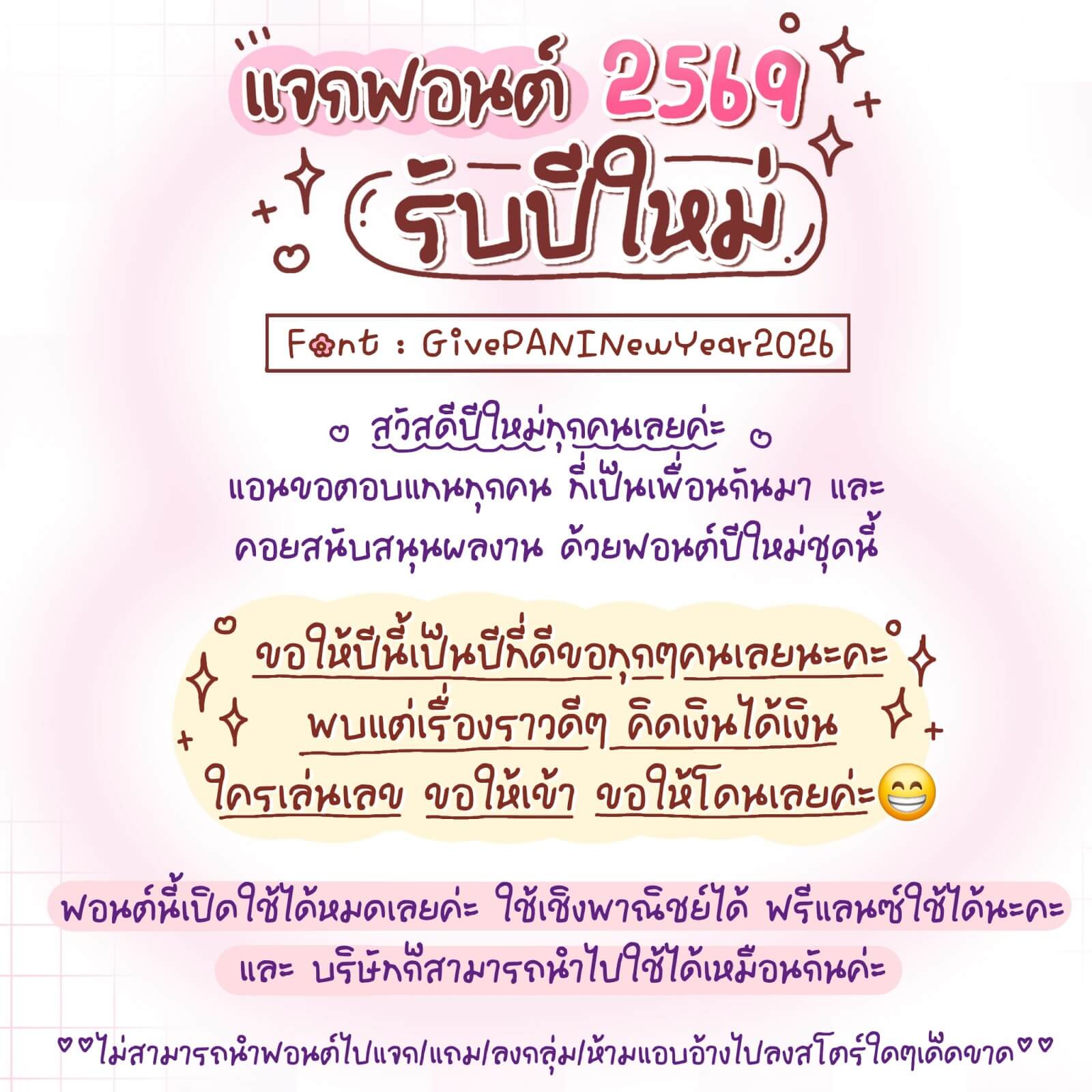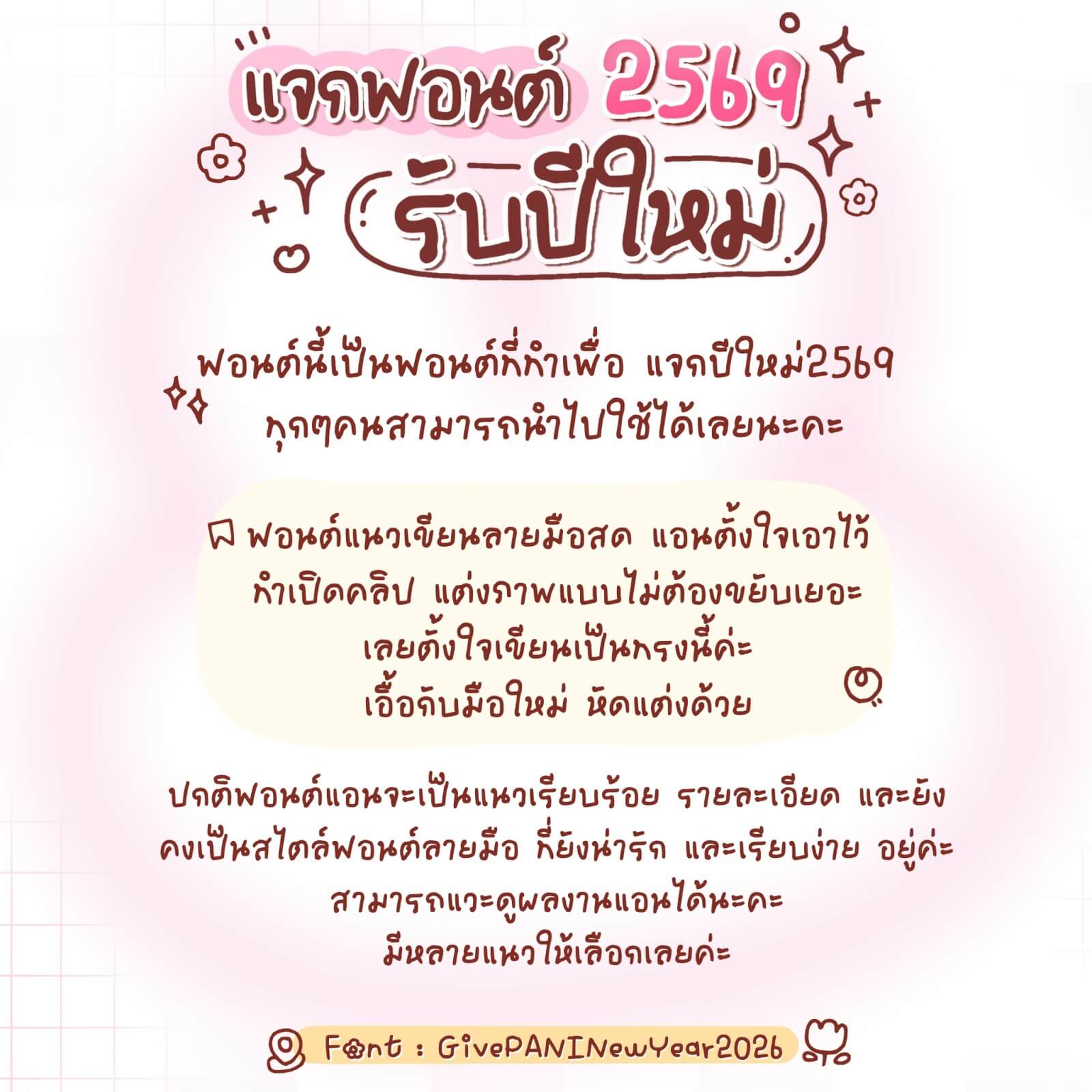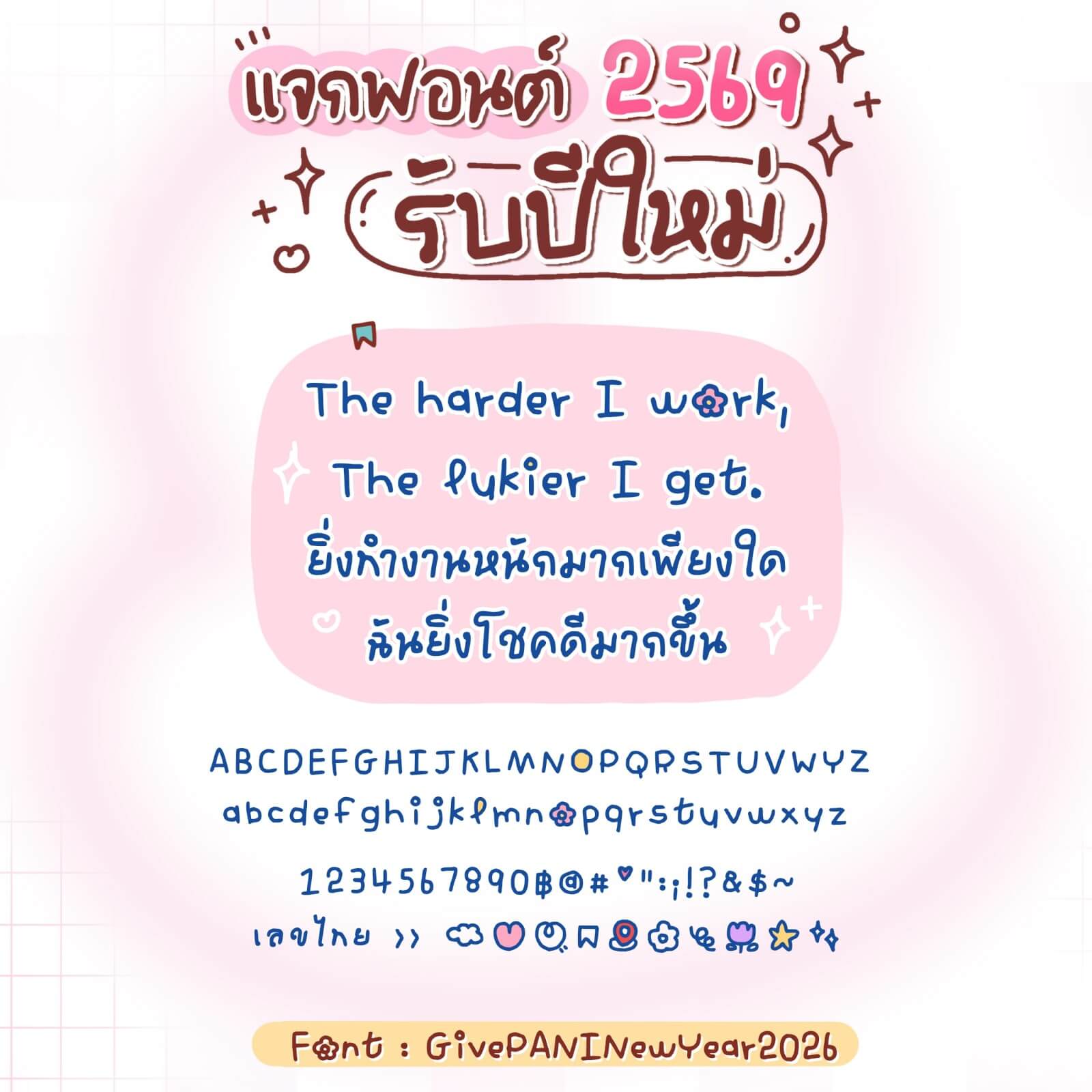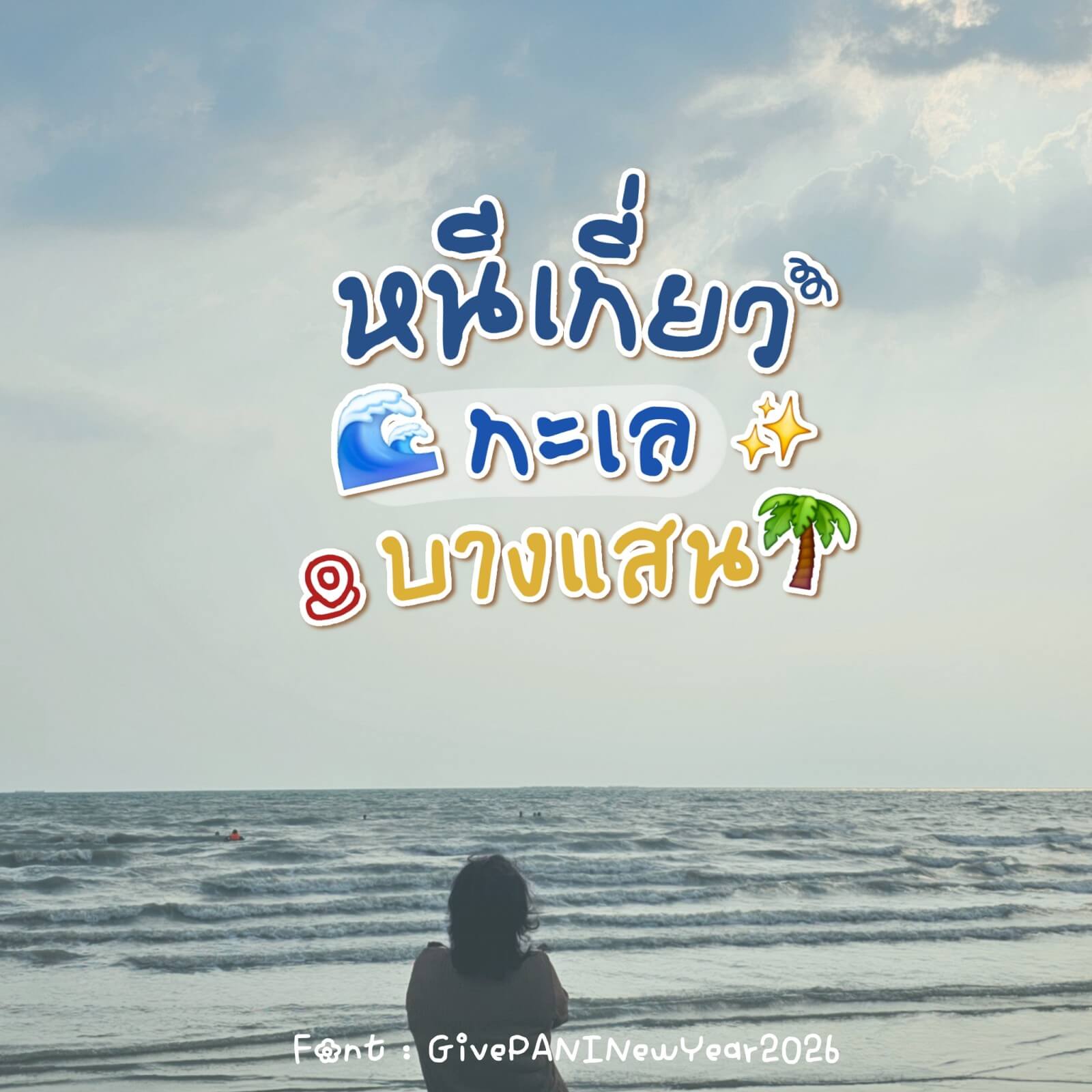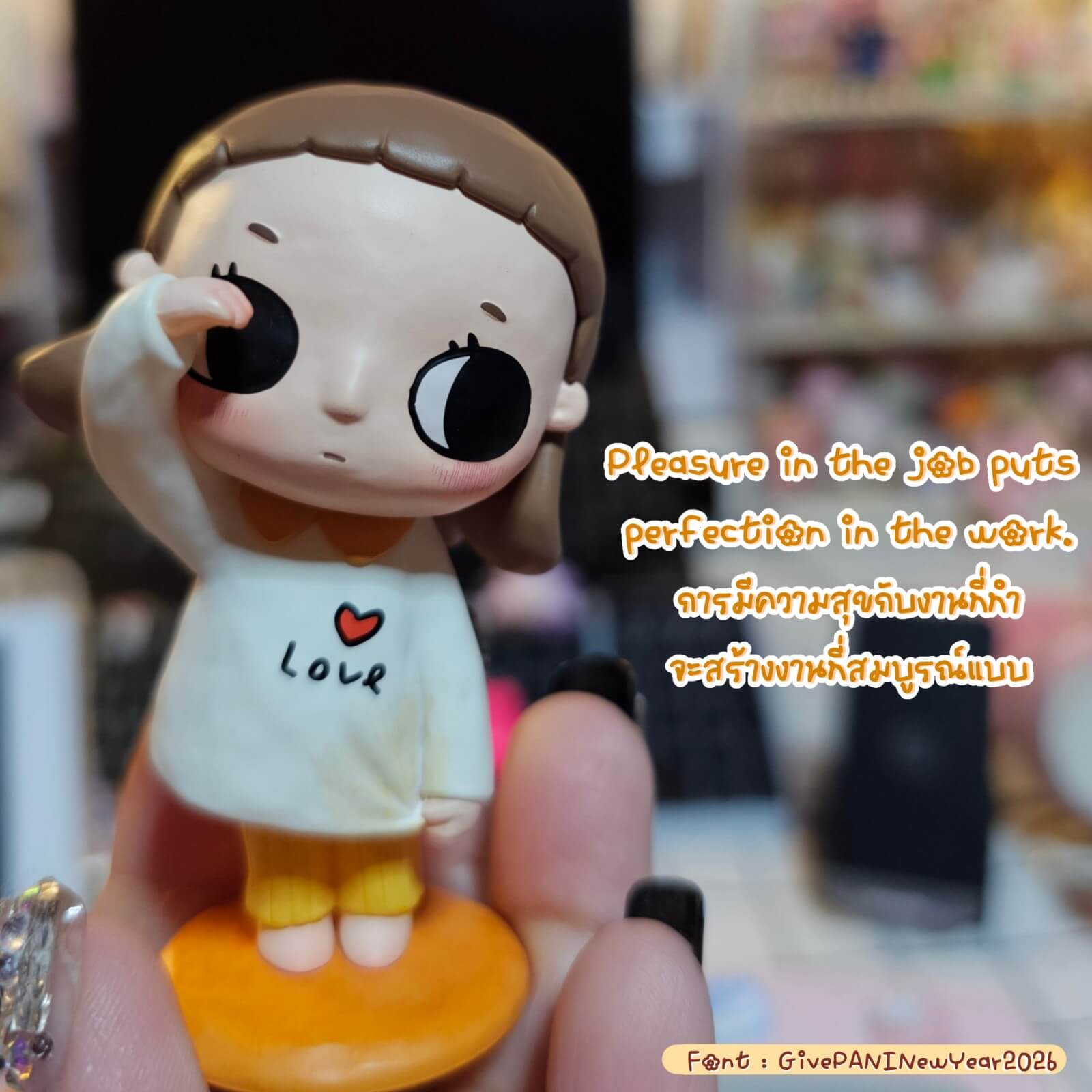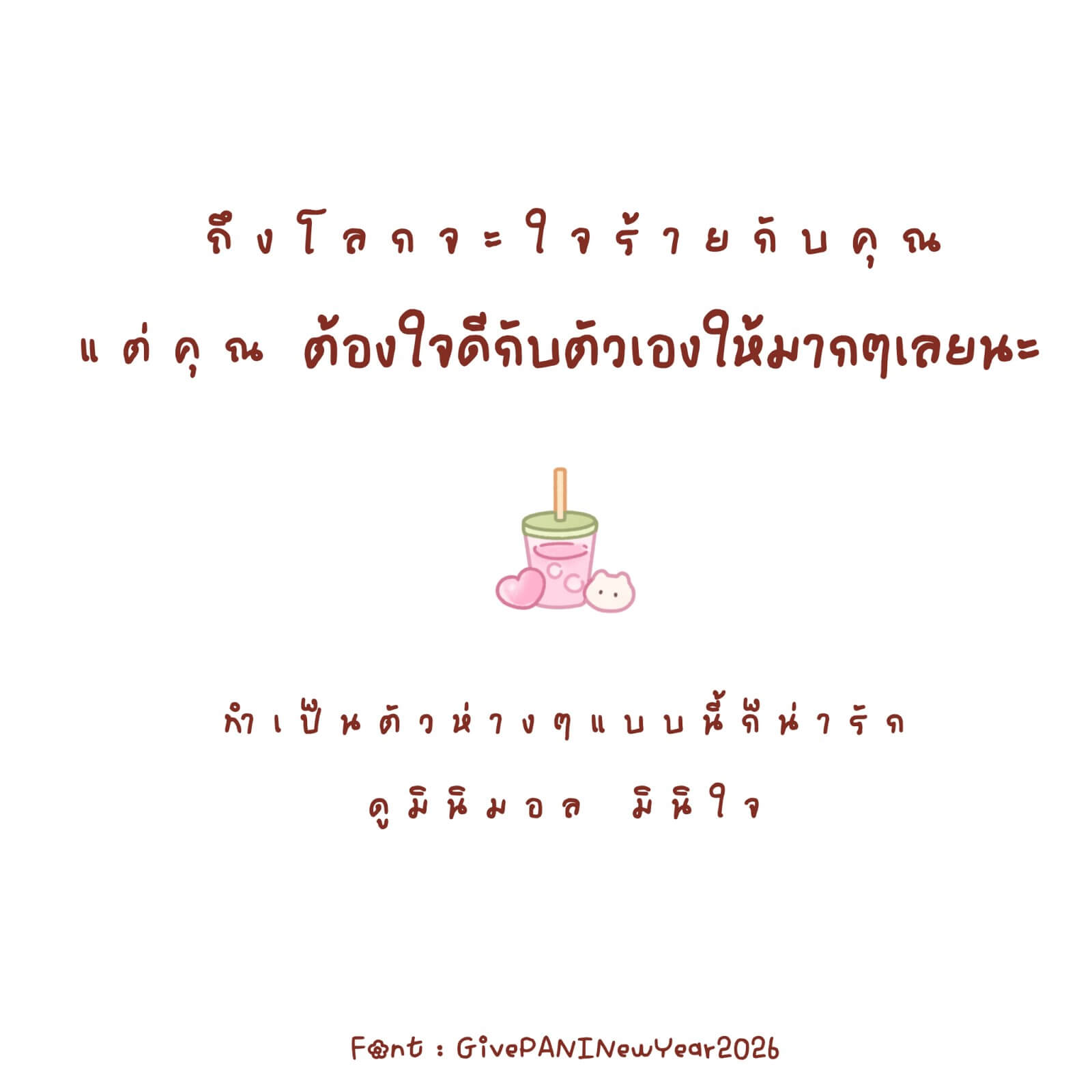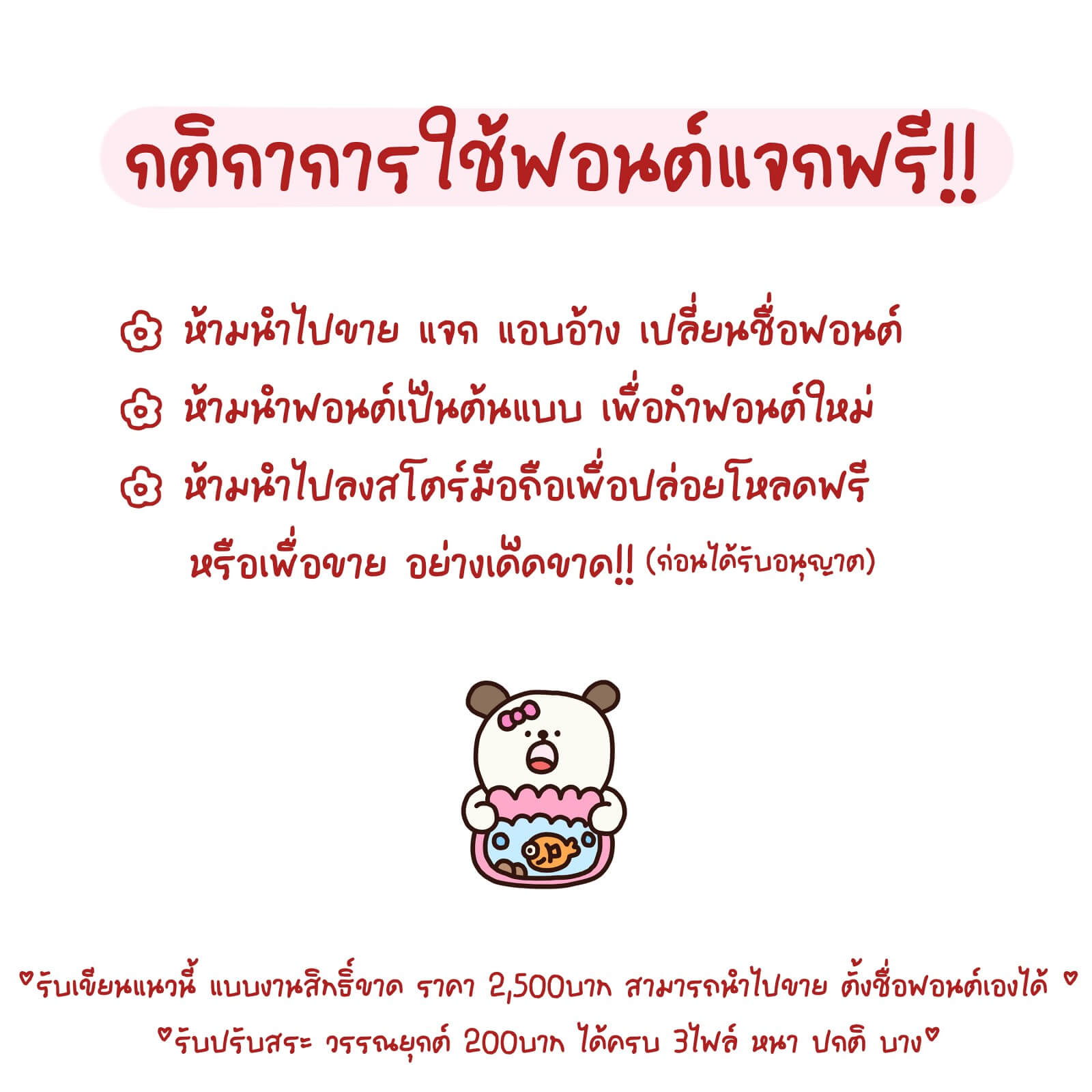
GivePANINewYear2026
ฟอนต์นี้เป็นฟอนต์ที่แอนทำเพื่อแจกปีใหม่ 2569 ทุกๆ คนสามารถนำไปใช้ได้เลยนะคะ
นายหน้ามือใหม่ อยากลองแต่งเปิดคลิปด้วยตัวเอง แนะนำเลยค่ะ แอนตั้งใจทำมาเพื่อพวกคุณเลย^^/
(แอนเข้าใจบางคนที่ยังไม่มีงบ กลัวซื้อแล้วจะทำไม่เป็น แต่การเลือกฟอนต์ เปิดคลิป มีผลทำให้คลิปน่าสนใจขึ้นได้จริง แอนเลยเขียนแนวๆ นี้มาค่ะ โหลดไปลองใช้กันดูนะคะ)